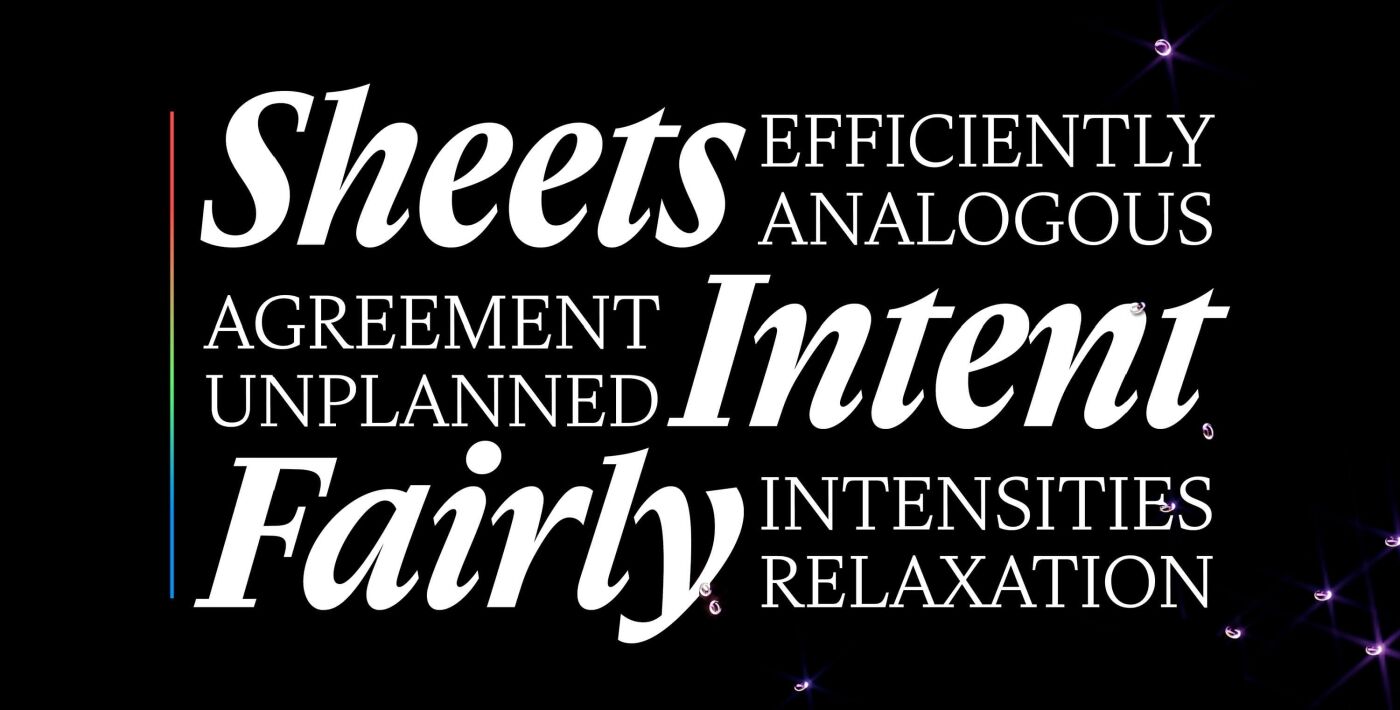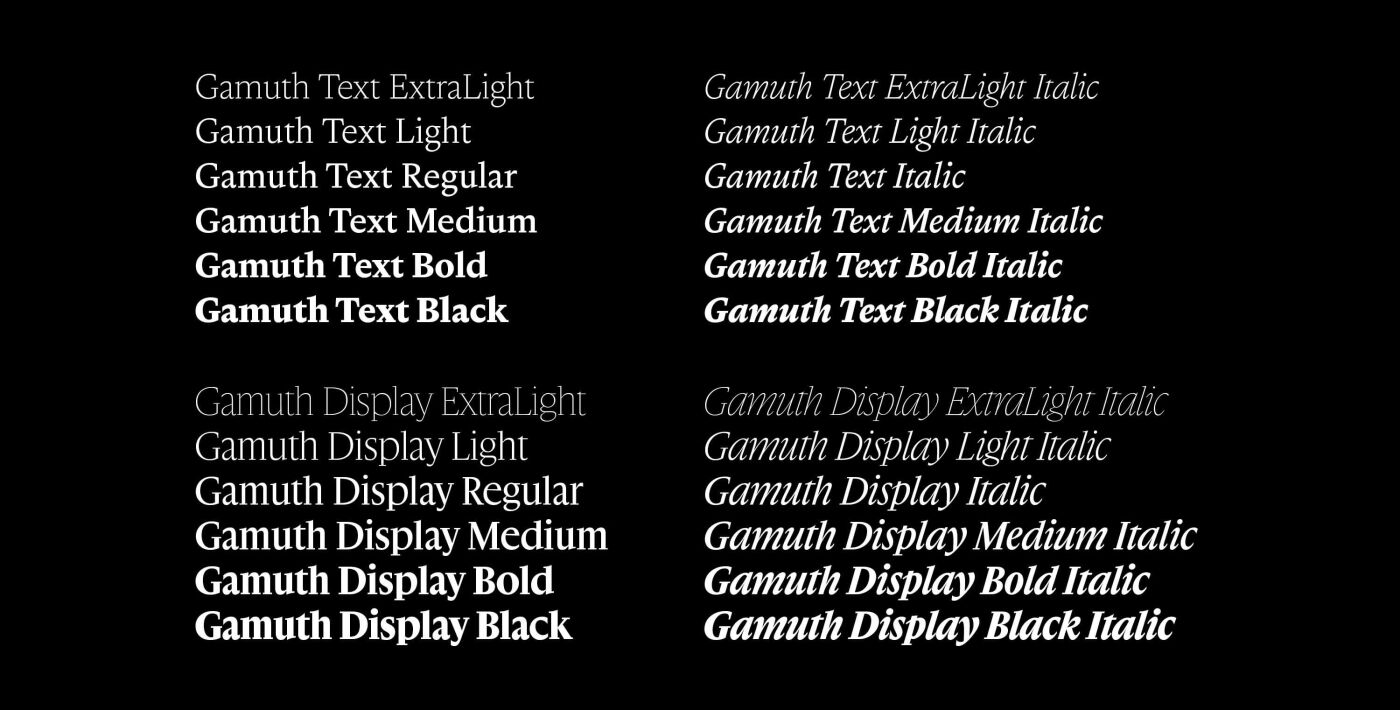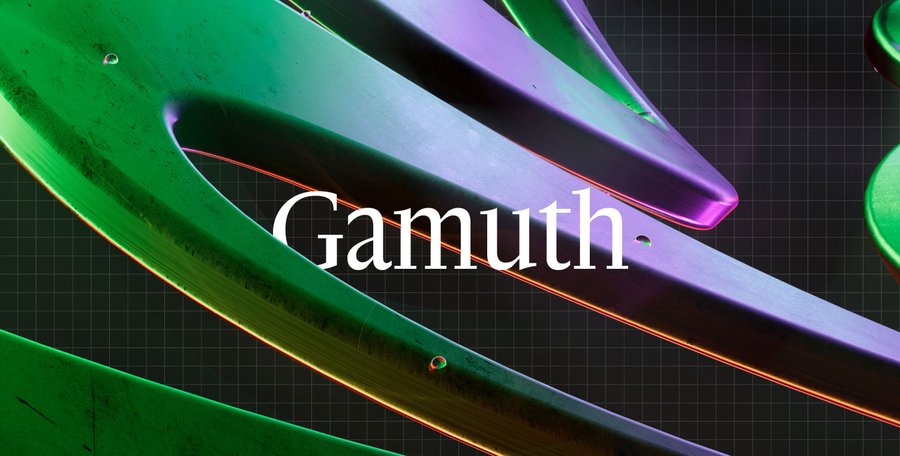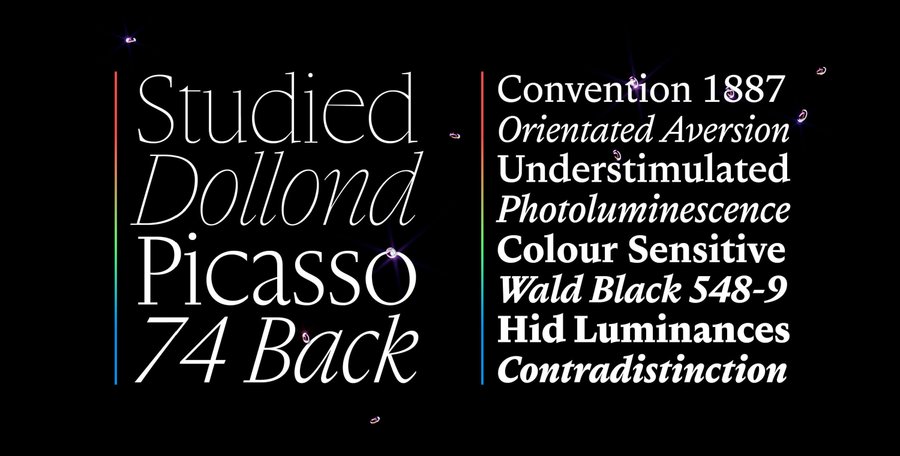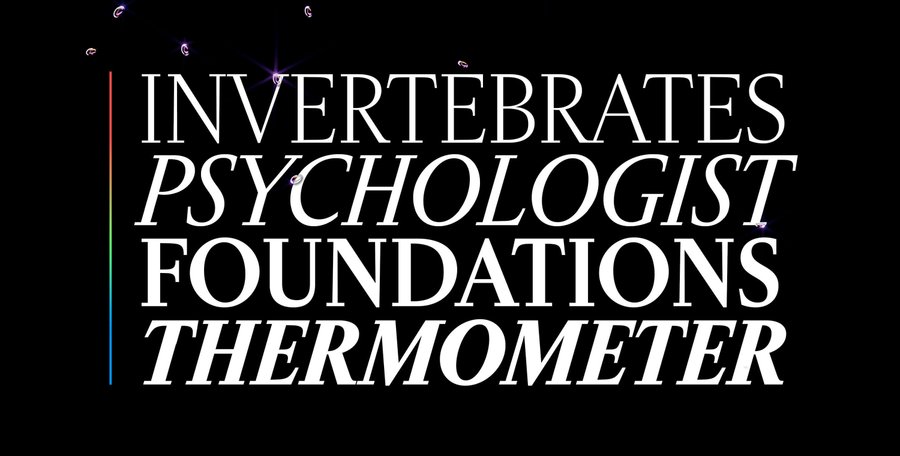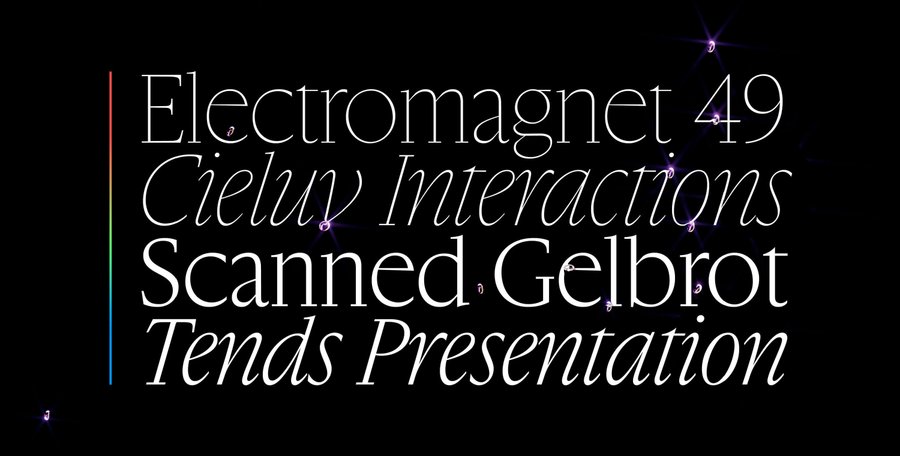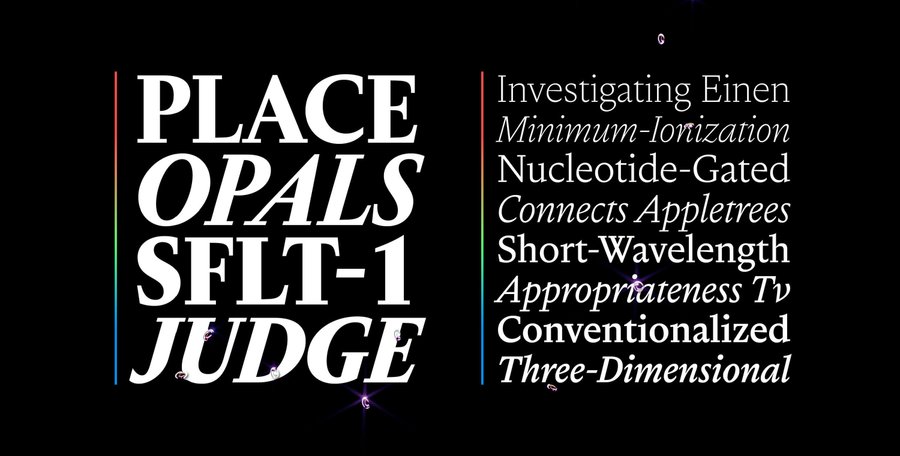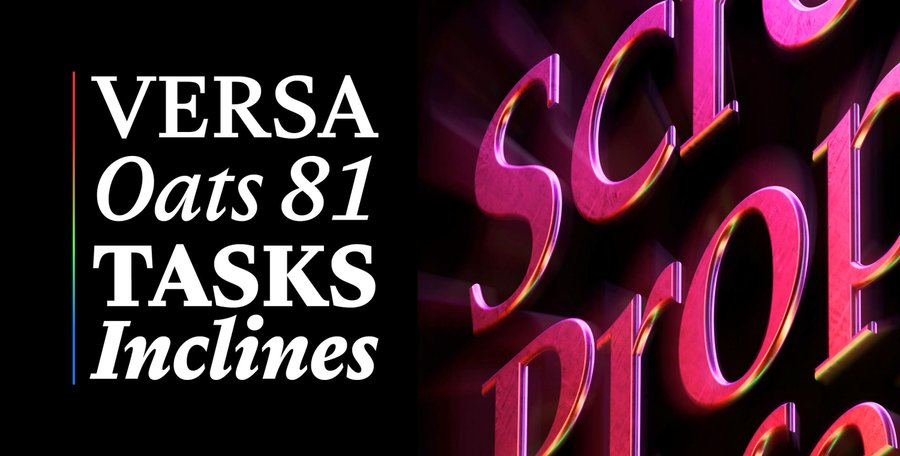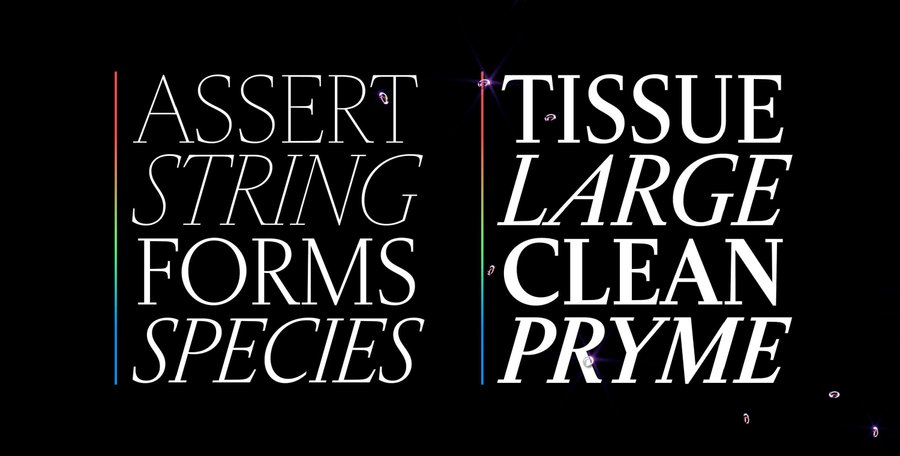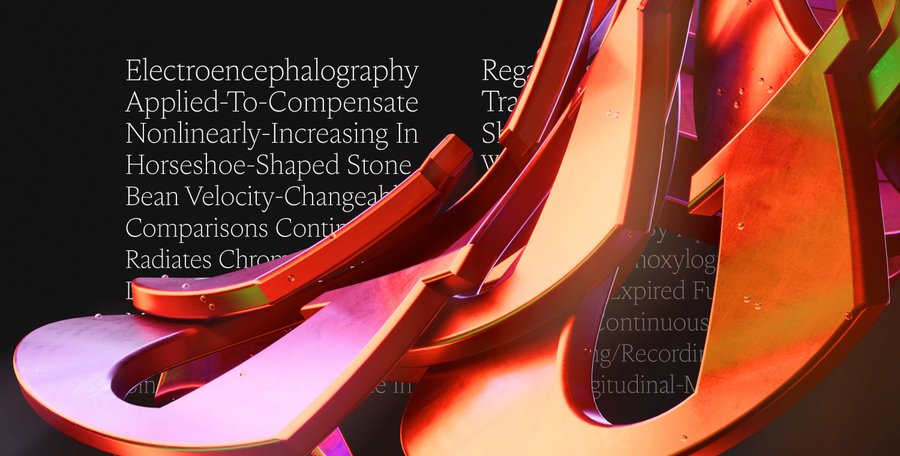
Gamuth
Gamuth est une famille de caractères à empattement disponible en deux tailles optiques : Text et Display. Elle s'inspire des polices baroques néerlandaises, mais avec des contours nets, conçus pour s'intégrer parfaitement dans l'environnement numérique contemporain.
Gamuth a également un companion sans-serif: Gamuth Sans